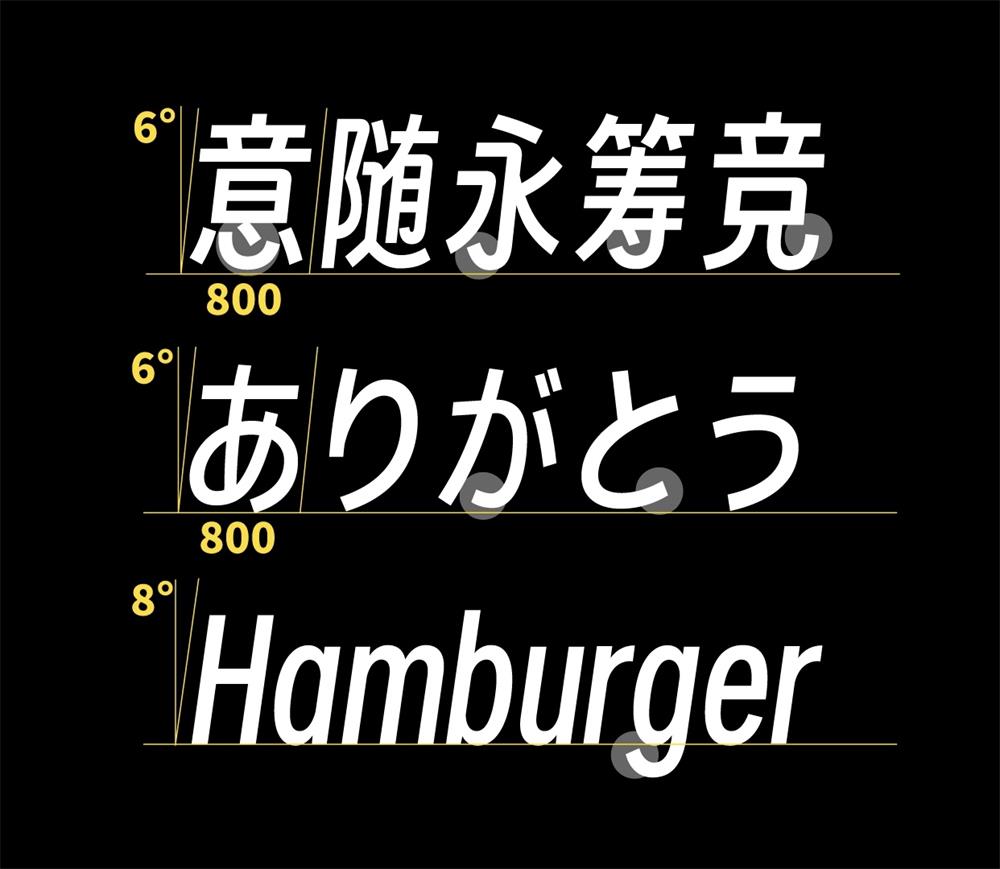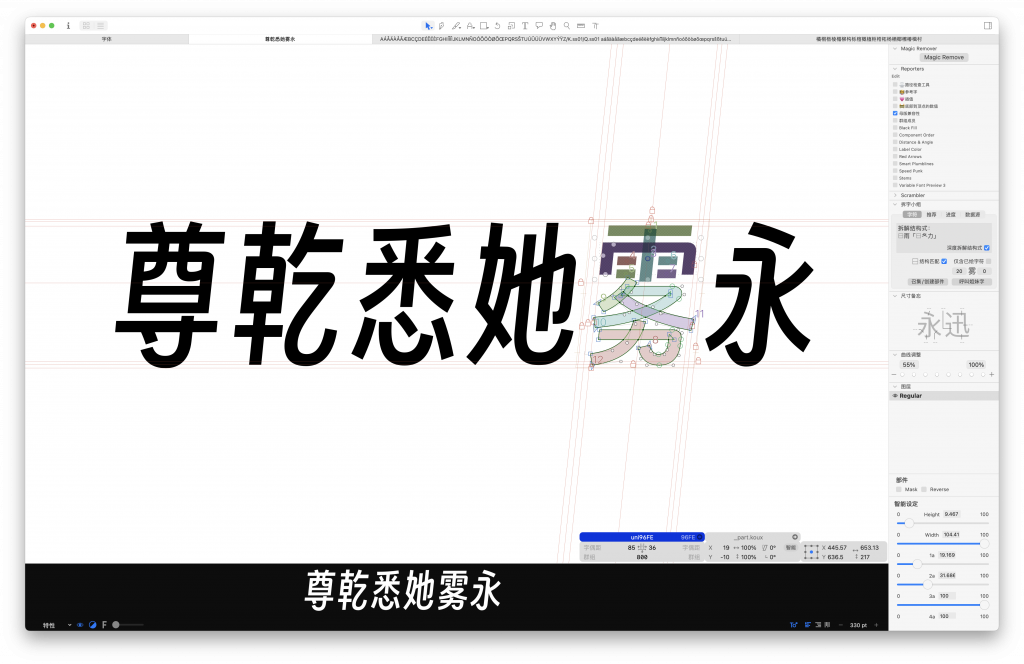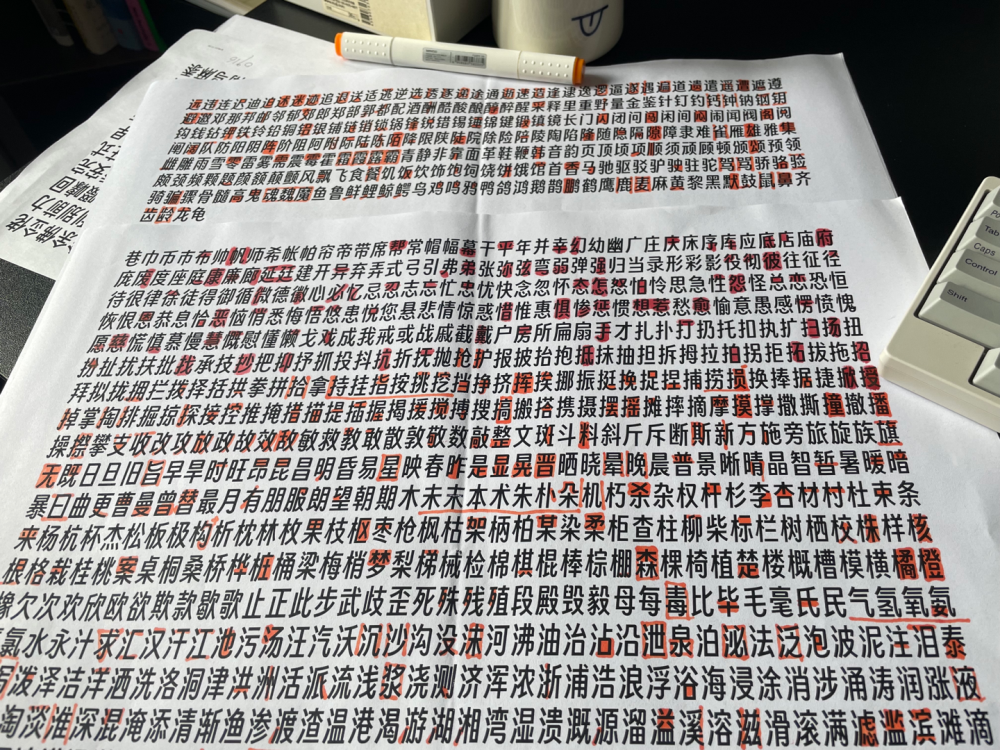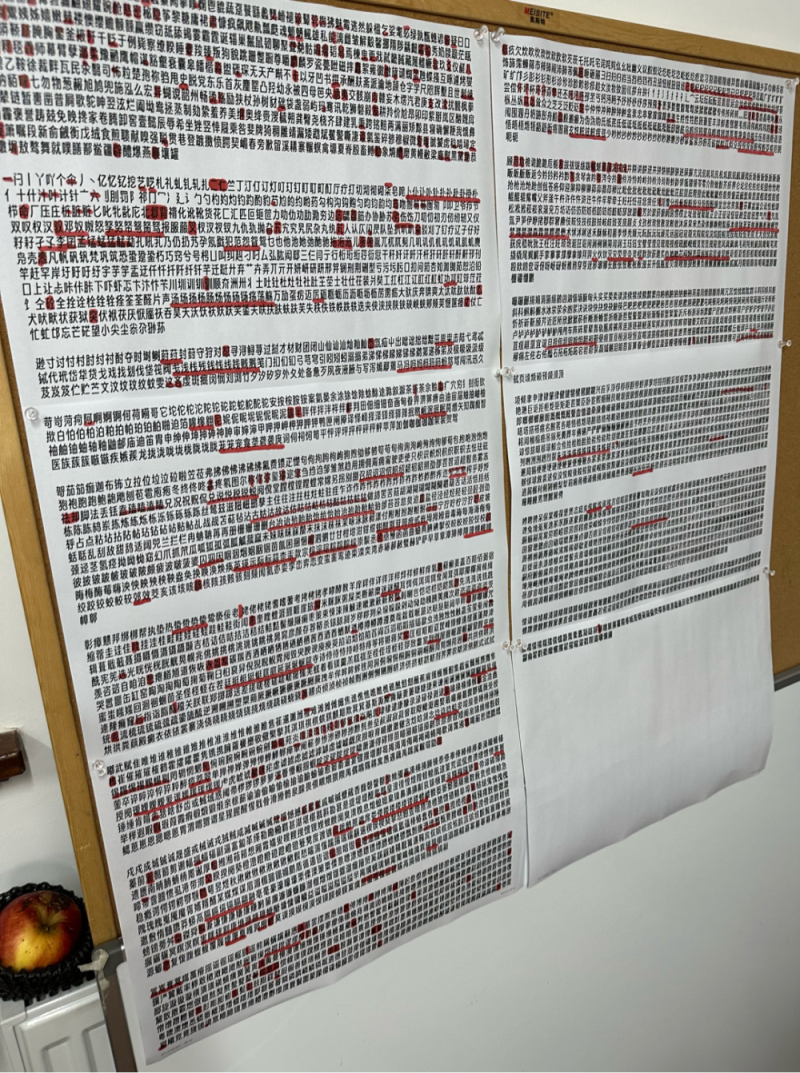
这是我以oooooohmygosh身份发布的第一款字体,11月15日正式开源发布,大家可以免费商用无任何限制,也可以修改创作。说个不太切实际的梦想,我希望以这个身份发布的所有作品,都是开源或者公益的。 这套字经过我和其他字体设计师伙伴们一年多的波折,终于要面世了。这款字虽然是美术字,但却是一个有挑战的命题。因为它有三个特征「大弧线、窄、斜」,每一项都很难做好。更何况把它们仨融合到了一起,还要去追求稳、匀、整……
“得意黑 斜体”是一款书写很新颖的字体,字体大方,适合各种设计作品使用!欢迎下载!